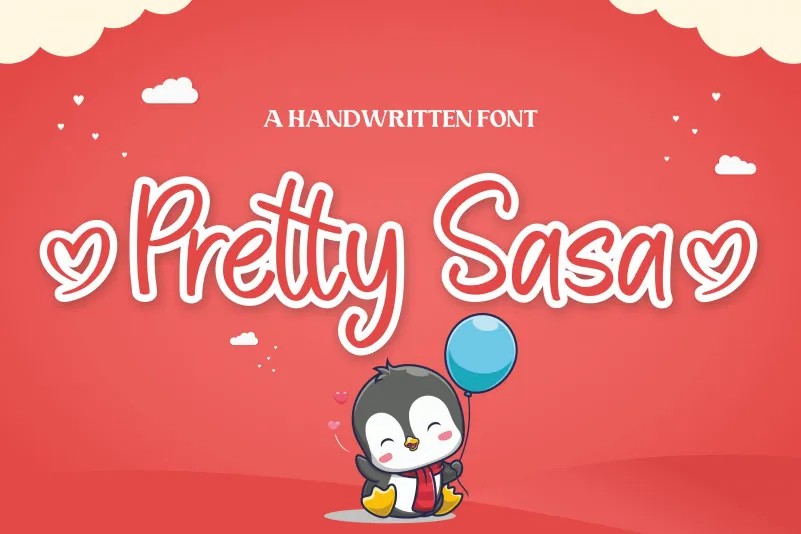
A “Pretty Sasa Font” é uma elegante fonte escrita à mão que traz uma sensação encantadora para qualquer projeto. Desenvolvida pelo Paily Studio, essa font é especialmente criada para os amantes do estilo a mão livre que desejam adicionar um toque único e encantador às suas criações digitais. Uma das características mais interessantes da “Pretty Sasa Font” é seu PUA (Private Use Area) codificado, o que permite uma facilidade incrível em acessar todos os caracteres e estilos especiais desta fonte. Se você gosta de explorar sua criatividade e deseja ter a chance de testar essa fonte para criar algo realmente único, essa é uma ótima oportunidade. Tente “Pretty Sasa Font” e deixe-se impressionar por todas as possibilidades que essa fonta encantadora oferece em suas criações digitais.